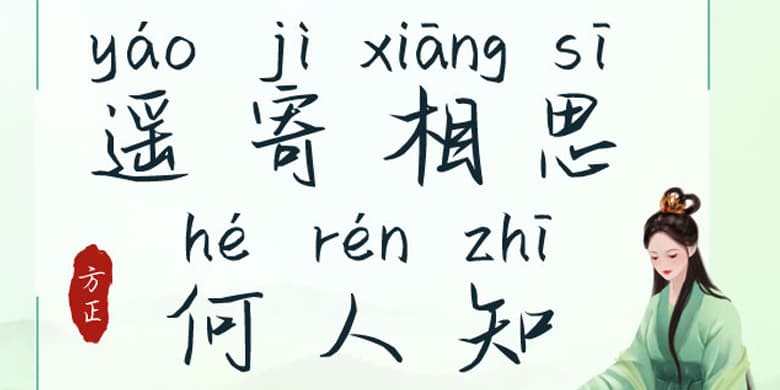
品牌:方正手迹设计师:宋昱东发行时间:2020字库编码:大陆简体(GB2312-80)分类:常规书写·硬笔字体属性:精品字
该字是一款行书字体加拼音,该款行书字体中宫较为收敛,用笔洒脱飘逸。加上易于辨识的拼音,具有良好的阅读体验。适用于文艺类的书刊、品牌广告和产品包装设计,以及社交网络的个性化用字。